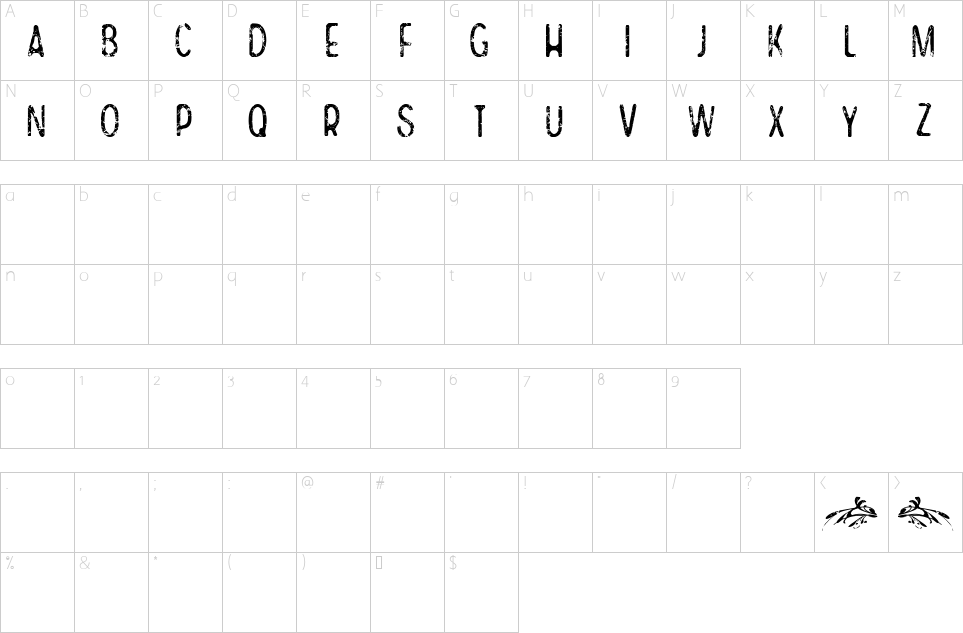
Descubra a fonte “Same Old Story” gratuita disponível para Windows e Mac. Esta fonte foi projetada por CloutierFontes e já foi baixada 6,679 vezes. “Same Old Story” é uma fonte moderna e dinâmica que pode dar um toque interessante às suas criações. Seja você um designer ou um amante de design, essa fonte pode ser uma ótima opção para adicionar um toque único ao seu próximo projeto. Ela combina facilmente com vários estilos e tamanhos de texto, tornando-se uma fonte versátil para todos os projetos digitais.